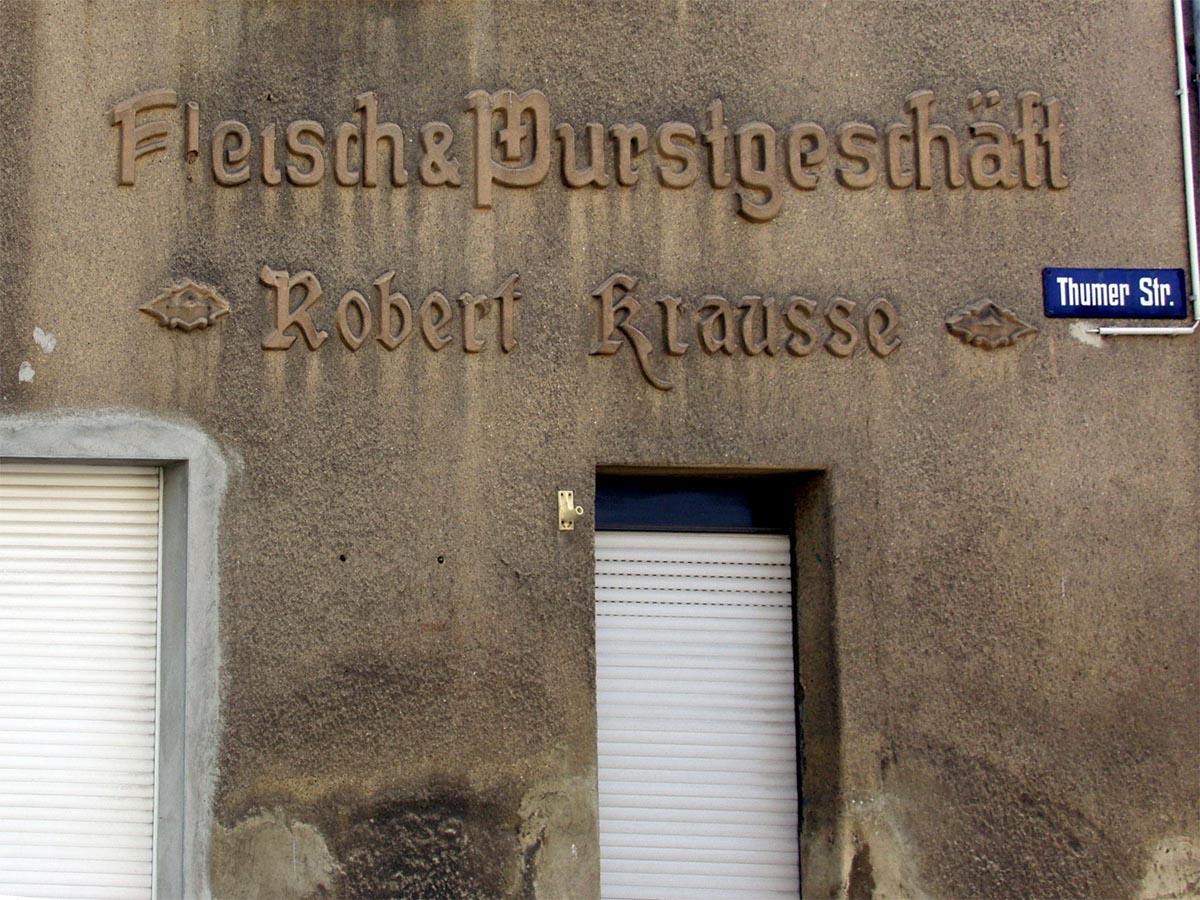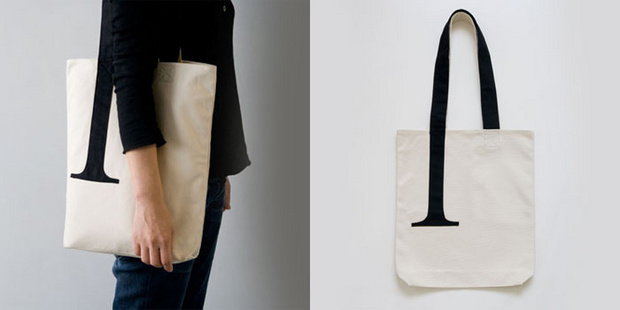
Wenn die Blechdose für die Maskenbrille authentisch ist, also aus der Zeit, da Soldaten und Zivilisten mit Gasmasken ausgerüstet wurden UND man Fraktur allgemein benutzte, dann frage ich mich (nee, Euch !) warum kein lang-s im Wort Maske steht.
(Und wie baue ich hier das schöne schlanke Lang-s ein??)
Wenn die Blechdose für die Maskenbrille authentisch ist, also aus der Zeit, da Soldaten und Zivilisten mit Gasmasken ausgerüstet wurden UND man Fraktur allgemein benutzte, dann frage ich mich (nee, Euch !) warum kein lang-s im Wort Maske steht.
(Und wie baue ich hier das schöne schlanke Lang-s ein??)
Tja, die S-Regeln in der traditionellen Rechtschreibung sind nicht so einfach, da gibt’s einige Ausnahmeregeln. So steht das Schluß-s ausnahmsweise auch am Silbenende (obwohl dort kein Wortteil endet), wenn die nächste Silbe mit d, k, m, n oder w beginnt. Beispiele: Dresden, Maske, Kosmos, Mesner, Oswald. Und das Schluß-s steht sogar im Auslaut vor k, obwohl dort weder ein Wortteil- noch ein Silbenende ist! Betroffen sind davon meines Wissens nur die beiden Wörter brüsk und grotesk.
Leider nicht notiert, wo das war. Gibt es hier eigentlich schon einen Thread für historische Façadenschriften?
Typographisch gibt es hier natürlich einiges zu mäkeln — das fehlende Divis, die fehlenden Abstände, die oben eingespart wurden, um dann offensichtlich unten verwendet zu werden, um ein riesiges Loch in den Namen zu reißen …
Dafür sind die ch-Ligaturen allerliebst und alle Fehler haben den Charme nicht zerstören können, den das Ding insgesamt verströmt.
Das »W« ist auch toll!
Ja, gefällt mir ziemlich gut – da passt ein Buch rein, ne Flasche Eistee, und dann ab in den Park, stylish aussehen ... ;-)
Zum stylisch aussehen im Park wird es dort sicher an fachkundigem Publikum fehlen. Das wird nur auf Typokonferenzen funktionieren.
Gibt es die Tasche eigentlich nur in Times semibold oder kann man zwischen Times, Janson, Garamond und noch ein paar anderen (jeweils in verschiedenen Schnitten) wählen?
Stimmt ja – Caecilia?
Gibt es die Tasche eigentlich nur in Times semibold oder kann man zwischen Times, Janson, Garamond und noch ein paar anderen (jeweils in verschiedenen Schnitten) wählen?
Leider nicht, aber es gibt eine Tasche™, Upper- und Lowercase Schals und noch mehr abgefahrenes Zeug ... Ich glaub da muss ich gelegentlich mal ne kleine Bestellung machen ... ;) Kuckt ihr hier.
@ Minimalist: Fashion Victim ;-);-);-)
… Upper- und Lowercase Schals …
Mit denen friert man bestimmt nicht …